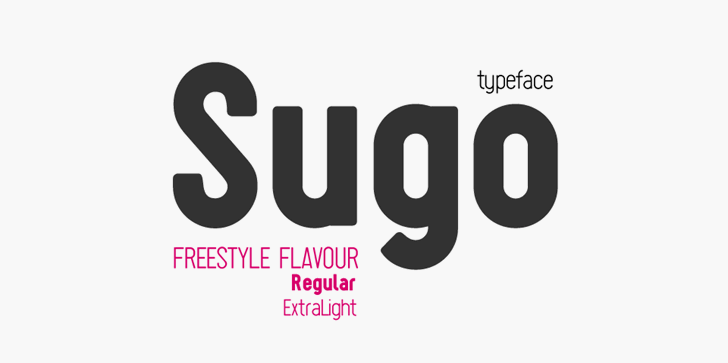
Sugo é uma tipografia sans-serif desenvolvida especificamente para a marca de uma loja de patins. Ela tem uma aparência direta e bruta, característica dos logotipos de lojas de skate. Sua forma retangular transmite um estilo desbragado e urbano, combinando perfeitamente com o espírito da cultura do skate. A leitura clara e a sensação contemporânea tornam Sugo a escolha perfeita para combinar personalidade e dinâmica em designs comerciais. Para uso comercial, é necessário obter uma licença no site oficial de Zetafonts: http://www.zetafonts.com/sugo. Para perguntas, utilize o e-mail .